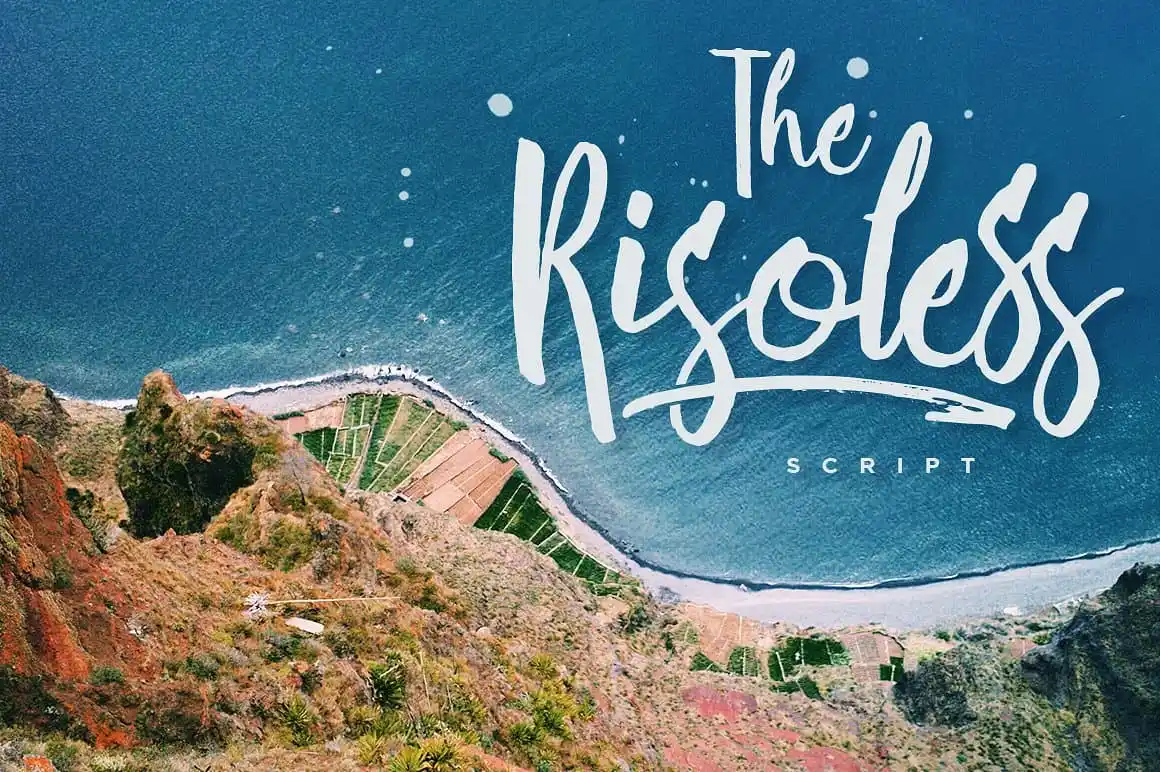
Introduzimos a Risoless Script Font ! Desenvolvida pelo estúdio Konstantine Studio, esta é uma fonte premium que você pode encontrar na plataforma Creativemarket. Desde seu lançamento inicial, foi um grande passo para tornar o Risoless Script livre de download hoje. A Risoless Script se baseia no movimento fluido da escrita a mão infantil e traduz esse estilo em uma fonte mantendo as honestidade e a adorável doçura em cada traço. Esta font vem completa com letras maiúsculas, minúsculas, números e pontuação. É compatível com o idioma de teclado padrão inglês. Conforme a descrição original, esta é uma ótima opção para quem busca um estilo artesanal e delicado em suas criações digitais.